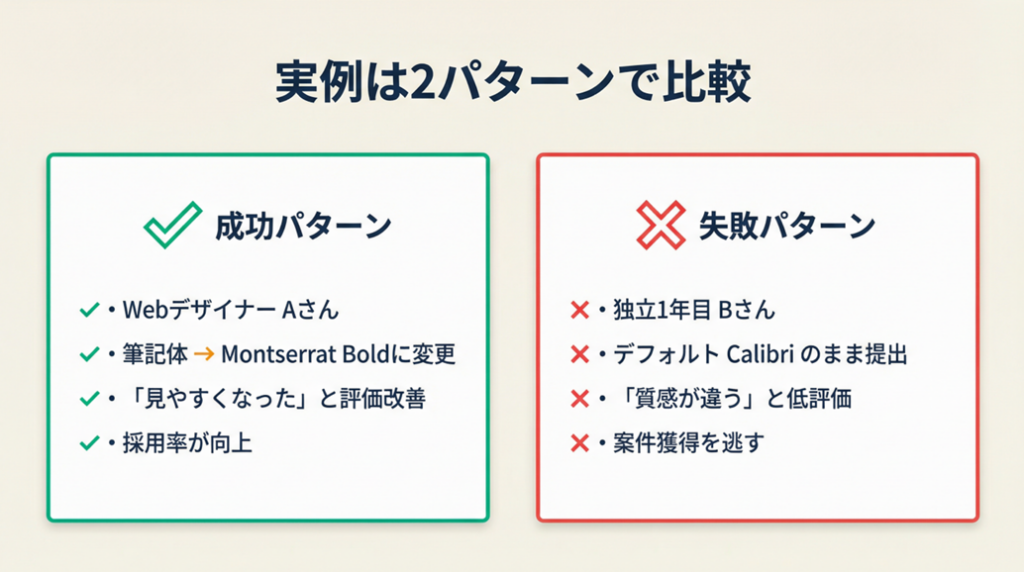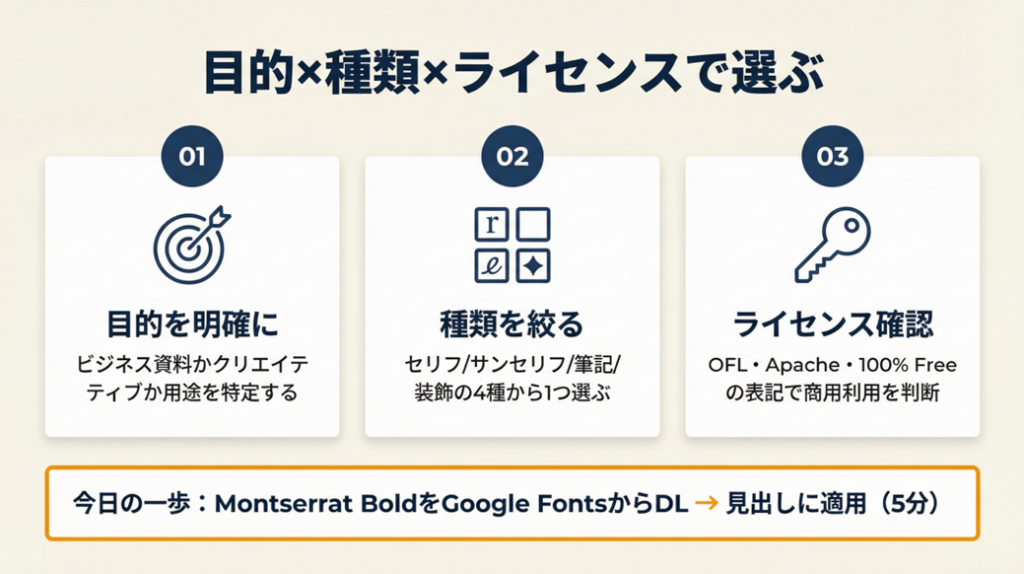
フリーランスの資料やロゴに使える「かっこいい英語フォント」は、無料&商用利用可能なものだけで10選以上あります。フォント種類の基本から用途別の選び方、パワポ・Canvaへの導入手順まで、この記事で一気に解決できます。
この記事の結論
かっこいい英語フォントを選ぶ鍵は「目的×種類×ライセンス」の3点確認です。Google FontsとDaFontを起点に目的に合う種類を絞り込み、商用利用の可否を利用規約で確認してからダウンロードすると、失敗なく導入できます。デフォルトフォントのまま使い続けると資料の印象が弱くなるため、用途に合ったフォント1本に変えるだけで制作物のクオリティが大きく変わります。
英語フォントは4種類で用途が決まる
まずは種類を4つに絞り込むと、用途に合った選択ができます。
セリフ体は信頼感が必要なビジネス文書向き
セリフ体は文字の端に「ひげ(serif)」が付いたデザインで、Times New RomanやGeorgiaが代表例です。視線の流れを誘導する効果があり、長文の読みやすさに優れています。つまりレポートや契約書、会社案内など「信頼性を伝えたい」場面で選ぶと、文字だけで誠実さが伝わります。
サンセリフ体はプレゼン資料やロゴに適している
ひげのないすっきりとした字形で、ArialやHelveticaが代表例です。モニター表示での視認性が高く、遠くから見る資料にも適しています。フリーランスが作るプレゼン資料やサービス紹介のチラシには、サンセリフ体を選ぶと現代的で洗練された印象を与えられます。WindowsにはArial(Microsoft社デフォルト収録)、Macには San Francisco が標準搭載されています。
グラフィックデザインの仕事内容でもサンセリフ体は基本フォントとして使われており、デザイン系の職種では特に重要な知識です。
筆記体は見出し・ロゴタイトルに限定して使う
筆記体(スクリプト体)はおしゃれな手書き風デザインが魅力ですが、本文に使うと読みにくくなります。
筆記体は見出し・ロゴ・サムネイルのタイトル部分のみに留め、本文にはサンセリフ体を組み合わせると読みやすさが保てます。これが「筆記体はやらなくてよい場所がある」と理解する最初の一歩です。
装飾体は印象を瞬時に変えるが使用は1点集中で
アウトラインや3D風、ステンシル風など個性が強い装飾体は、インパクトを与えたい箇所に1点だけ使うのが鉄則です。複数箇所に使うと統一感がなくなり、アマチュア感が出てしまいます。「見出し1か所のみ」という制約を設けると、資料全体が締まります。怖いフォントや個性的な装飾体を用途別に選ぶ方法については、怖いフォント無料10選でも詳しく解説しています。
CHECK
-> フォント種類(セリフ/サンセリフ/筆記体/装飾体)を確認し、自分の制作物の目的に合う1種類を選ぶ(2分)
Q: セリフ体とサンセリフ体はどちらが資料向きですか?
A: プレゼン資料やデジタル表示にはサンセリフ体(Arial、Calibriなど)が適しています。印刷物や長文の読み物はセリフ体の方が視線の流れが自然になります。
Q: 筆記体フォントを本文に使っても問題ありませんか?
A: 本文への使用はおすすめしません。筆記体は装飾的で視認性が低く、プレゼンや資料では文字が読まれにくくなります。タイトルや見出し1行に限定して使うのが基本です。
英語フォントの用途を3分で診断
以下の質問に答えれば、適したフォントカテゴリを3分で絞り込めます。
Q1: 制作物の主な用途はどちらですか?
- ビジネス資料・プレゼン → Q2へ
- ロゴ・サムネイル・クリエイティブ → Q3へ
Q2: 資料の配布形式は?
- デジタル表示(モニター・プロジェクター)→ Result A
- 印刷物・PDF → Result B
Q3: ブランドトーンはどちらに近い?
- クールでモダン → Result C
- 手書き風でやわらかい → Result D
Result A: サンセリフ体(例:Montserrat、Noto Sans)
モニター表示の視認性が高く、スライドの遠投で読みやすい。Google Fontsで無料取得可能。
Result B: セリフ体(例:Playfair Display、EB Garamond)
印刷での読みやすさに優れ、格式のある印象を与える。長文レポートや会社案内に適しています。フリーランスの名刺デザインに活用するなら、セリフ体で格式を演出するのも有効な選択肢です。
Q: PowerPointのおすすめ英語フォントを教えてください。
A: 見出しにはMontserrat BoldまたはBebas Neue、本文にはNoto SansまたはOpen Sansが定番です。どれもGoogle Fontsから無料ダウンロードでき、商用利用も可能です。Calibri(Windows標準)はそのまま使っても可読性は高いですが、見出しだけでもBold系のサンセリフに変えると印象が変わります。
A: DaFont(筆記体カテゴリ)が種類の豊富さで最適です。商用利用する場合はライセンス欄が「100% Free」のものを選んでください。Google Fontsにも「Dancing Script」「Great Vibes」などの筆記体フォントが無料で提供されており、商用利用も問題ありません。